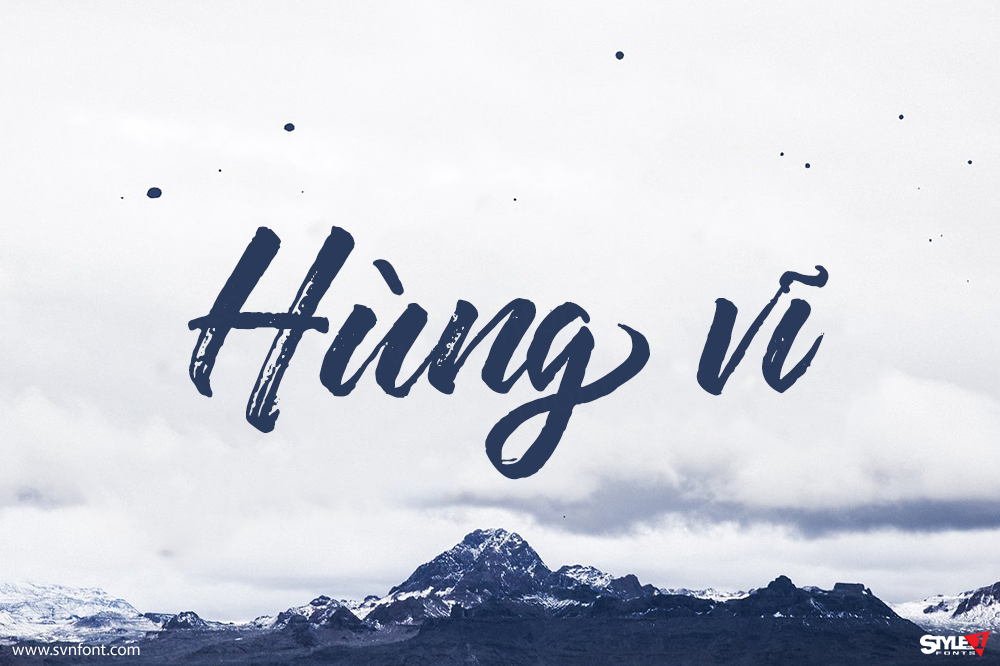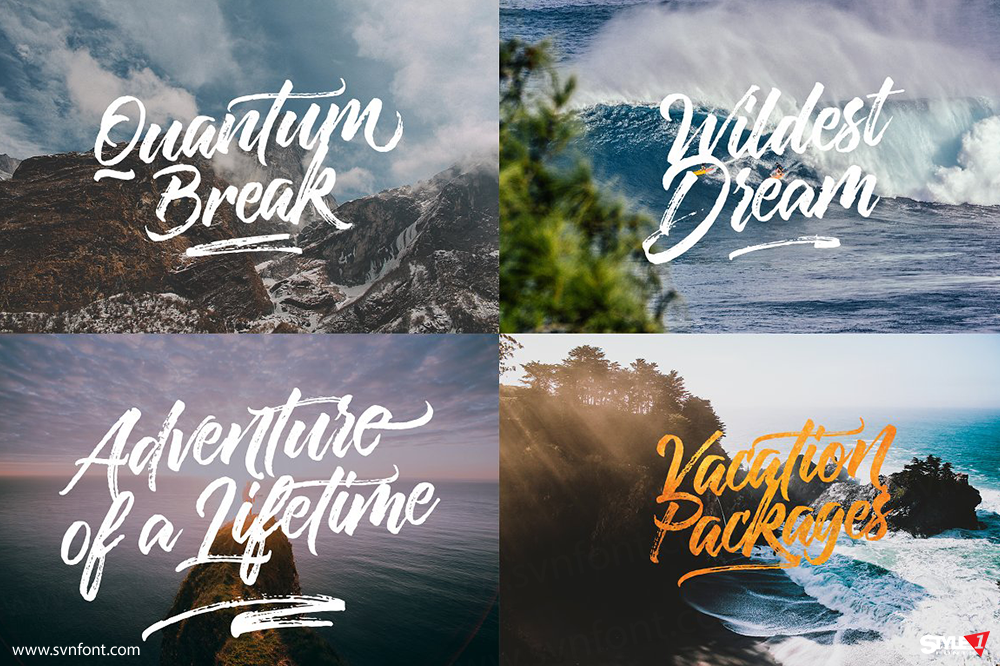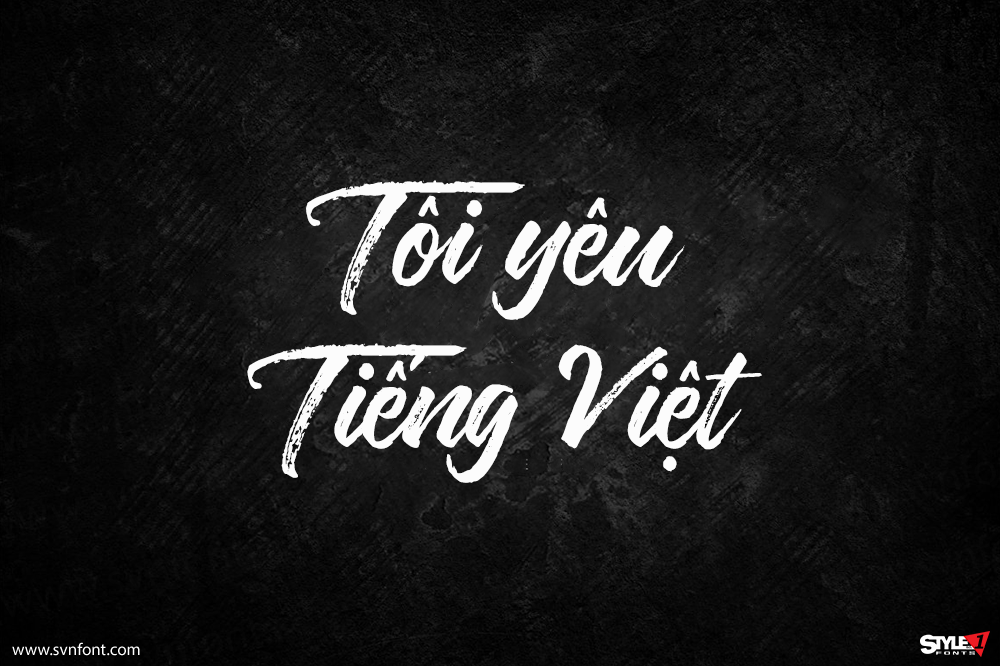
Twilight Script là một font brush khô mang phong cách viết tay, được thiết kế để kết hợp hài hòa và giúp bạn tạo hand-lettering ấn tượng một cách nhanh chóng, dễ dàng. Font rất lý tưởng cho logo, trích dẫn viết tay, bao bì sản phẩm, tiêu đề, poster, merchandise, mạng xã hội và thiệp chúc mừng.
Twilight Script bao gồm chữ hoa, chữ thường, bộ dấu câu phong phú, chữ số, hỗ trợ ngôn ngữ quốc tế, cùng stylistic alternates cho một số ký tự chữ thường quan trọng, mang lại sự linh hoạt và chiều sâu sáng tạo cho thiết kế.
Nhà thiết kế: Hermansyah Getstudio
Nhà phát hành: Hermansyah Getstudio